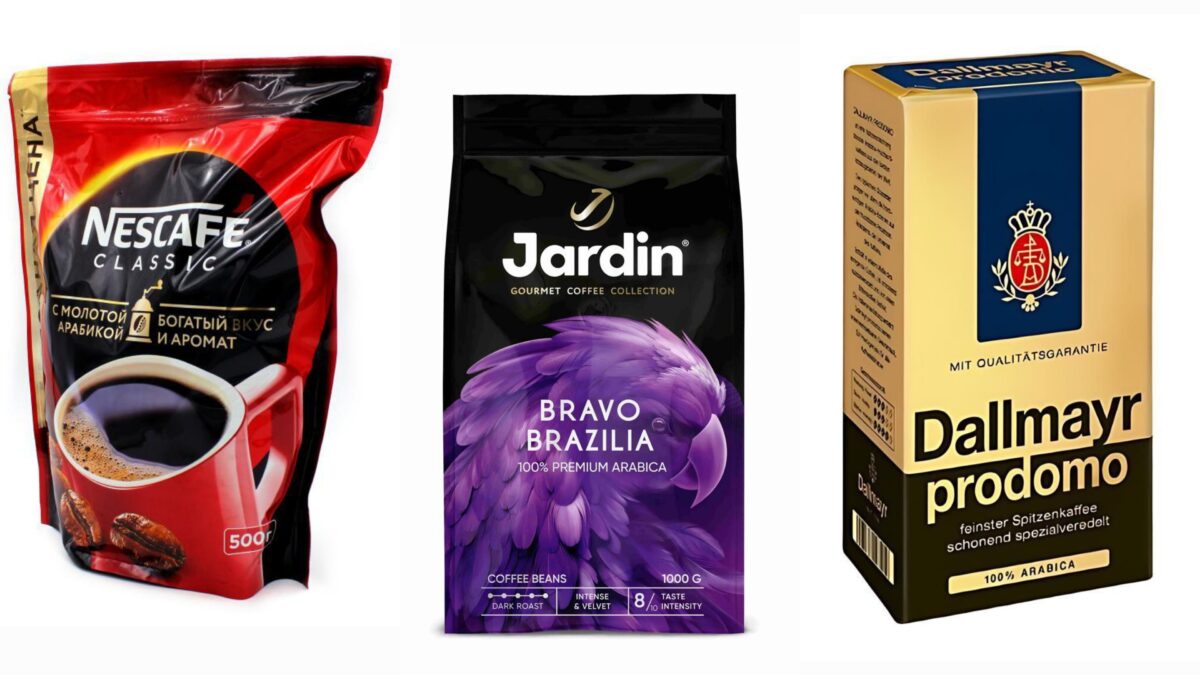
Шрифт как триггер: как форма буквы управляет доверием, аппетитом и ощущением времени
Введение
Мы редко задумываемся, почему один шрифт кажется «вкусным», другой — «дорогим», а третий — «надёжным». Но наш мозг считывает форму буквы быстрее, чем её содержание. Задолго до того, как мы осознанно прочитали слово, мы уже испытали эмоцию: доверие или тревогу, голод или равнодушие, ощущение скорости или покоя. Это не магия и не случайность. Это нейроэстетика шрифта — область на стыке типографики и психологии восприятия. Понимание этих скрытых механизмов превращает дизайнера из оформителя в инженера эмоций.
Почему форма важнее содержания
Человеческий мозг обрабатывает визуальную информацию в разы быстрее текстовой. Когда мы видим надпись, первым срабатывает не центр чтения, а древние отделы, отвечающие за распознавание форм и оценку угрозы. Острые углы = опасность (хищник, оружие). Мягкие округлости = безопасность (плод, лицо ребёнка). Вертикали и симметрия = стабильность. Асимметрия и наклон = движение. Эти ассоциации настолько глубоки, что работают мгновенно и безотказно. Шрифт — это упаковка смысла, и первое впечатление формирует именно упаковка.
Четыре триггера: как шрифт управляет восприятием
1. Округлость и сладость: триггер аппетита
Мягкие, округлые, «пухлые» шрифты (такие как Cooper Black, Lobster, Circe) почти безотказно вызывают ощущение чего-то съедобного, сладкого, тёплого. Их активно используют кондитерские бренды, кафе и производители детских товаров. Причина проста: круглые формы напоминают нам спелые плоды, хлеб, уютную выпечку. Посмотрите на логотипы Krispy Kreme, Dunkin’, «ВкусВилл» — везде доминирует мягкая округлость. Этот же приём работает на упаковке: шоколад в обёртке с округлым шрифтом кажется более нежным и сливочным, даже если рецептура не менялась.
2. Острота и скорость: триггер адреналина
Угловатые, скошенные, динамичные шрифты (курсивные гротески, геометрические рубленые с острыми углами) включают ощущение скорости, энергии и даже агрессии. Это язык спортивных брендов, автопрома и гейм-индустрии. Вспомните логотипы Nike, Puma, Lamborghini, PlayStation — везде острота и наклон создают импульс. Мозг считывает: «движение, опасность, адреналин». Дизайнер, понимающий этот триггер, никогда не поставит округлый дружелюбный шрифт на афишу гоночного события — и наоборот.
3. Засечка и серьёзность: триггер доверия
Антиква с выраженными засечками (Garamond, Times New Roman, Bodoni) десятилетиями ассоциируется с традицией, стабильностью и властью. Её выбирают банки, юридические фирмы, университеты и государственные учреждения. Почему? Засечки создают визуальный фундамент, опору, якорь. Они говорят: «мы здесь давно, нам можно доверять». Интересно, что этот триггер работает настолько сильно, что даже стартапы, желающие казаться солиднее, иногда используют антикву в логотипах. А её отсутствие в гротеске, наоборот, сигнализирует: «мы новые, современные, гибкие».
4. Тонкость и роскошь: триггер цены
Высокий контраст между основными и соединительными штрихами, тонкие засечки, изящные пропорции — это визуальный код премиального сегмента. Шрифты вроде Didot, Bodoni, Cormorant стали синонимом моды и дороговизны. Журнал Vogue использует Didot не потому, что он «красивый», а потому что его утончённые линии бессознательно считываются как хрупкая, драгоценная вещь. В дизайне упаковки этот триггер работает напрямую: один и тот же крем в банке с округлым гротеском будет восприниматься как масс-маркет, а в банке с контрастной антиквой и тонкими засечками — как люкс. Цена в голове покупателя изменится раньше, чем он прочитает состав.
Как это работает на практике: три кейса
Представьте три упаковки кофе.
Первая — бюджетная: плёнка, яркие цвета, сжатый жирный гротеск. Триггер — «доступность, акция, срочно купить».
Вторая — средний сегмент: крафтовый пакет, спокойный гуманистический гротеск, рукописный акцидентный элемент. Триггер — «честность, натуральность, уют».
Третья — премиум: чёрный матовый фон, золотое тиснение, изящная антиква с высоким контрастом. Триггер — «исключительность, церемония, статус».
Три продукта, один и тот же кофе внутри. Но цена в воображении покупателя отличается в разы. И эту разницу создаёт в том числе шрифт.
Заключение
Шрифт — это не носитель текста, а носитель эмоции. Понимание триггеров, зашитых в форму буквы, даёт дизайнеру власть над восприятием: он может сделать продукт аппетитным, бренд — надёжным, упаковку — дорогой. Это не интуиция и не «вкусовщина». Это система, которую можно изучить, проверить и применить. И когда вы в следующий раз будете выбирать гарнитуру для проекта, спросите себя не «красиво ли это», а «что почувствует зритель за долю секунды до того, как прочитает слово». Ответ на этот вопрос и есть суть дизайна.